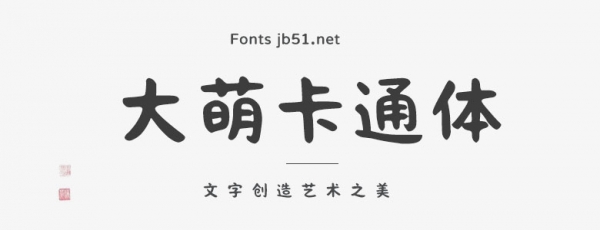
大萌卡通體是一款充滿童趣和創(chuàng)意的字體,每個(gè)字符都像是一個(gè)小小的卡通形象,線條圓潤(rùn)且富有彈性,仿佛每一個(gè)字母都有著自己的小情緒和小故事。這種字體通常用于兒童讀物、動(dòng)畫片標(biāo)題、廣告宣傳以及任何需要營(yíng)造輕松愉快氛圍的場(chǎng)合。